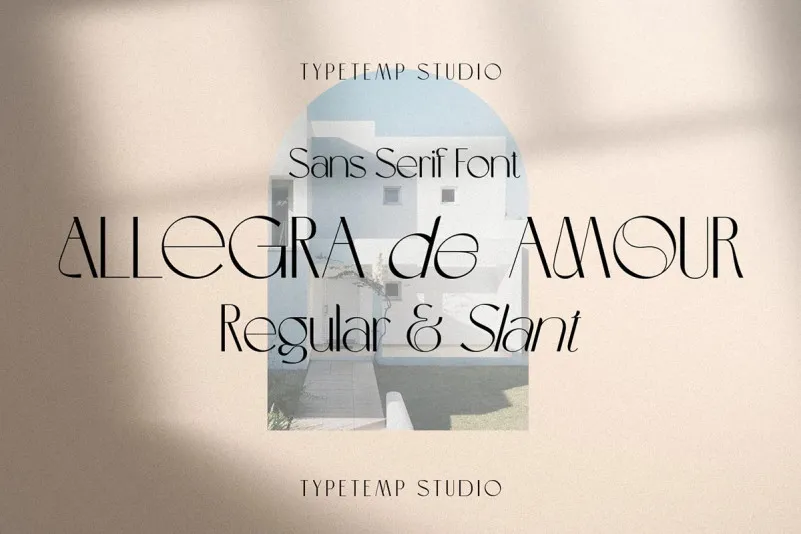
Allegra De Amour Font – Download Grátis
A fonte ‘Allegra De Amour Font’ é uma seleção pura de linhas sem serif que se destaca pelas suas formas leves e modernas. Esse tipo sans-serif é perfeito para projetos minimalistas e contemporâneos, oferecendo uma aparência elegante e minimalista que combina com design editorial ou criação de logotipos. Suas características OpenType permitem acesso a diversas alternativas de letras e ligaturas, o que lhe dá flexibilidade para personalizar a fonte da maneira que desejar, tornando-a ideal tanto para editoriais quanto para uso em peças de branding de roupas ou embalagens de produtos. Suas linhas sutis e limpas também se adequam perfeitamente a cabeçalhos de revistas, além de fornecer um texto elegante que pode servir como fundo para imagens em qualquer design gráfico.